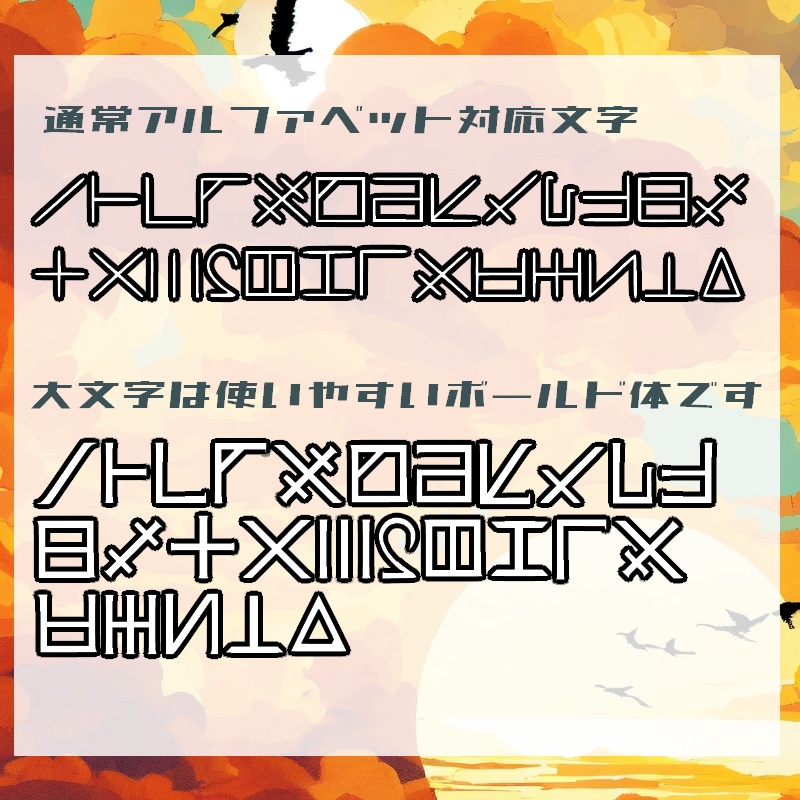
HYUPONIA FONT
『Hyuponia_Font』は風のクロノア2 世界が望んだ忘れ物 の作中,哀しみの国『フーポニア』で使用されている架空文字をフォントしたものです. 大文字は使いやすさ重視のアレンジボールド書体,小文字はゲーム中で哀しみの王様がスフィアに発現させている書体の再現になります. あくまで資料をやゲーム画面を元に再現したものですので,再現性の保証はしかねます. ご使用の際はその点を留意していただけると助かります. クロノア作品での創作活動などにお役立ていただけると幸いです. 対応文字や細かい仕様については同封のreadmeテキストを参照してください. 尚,このフォントは更新により内容が旧版から変化することがありますがご了承ください. (現行最新版はVer3です) =========================================== このフォントはデザイン用途にご使用いただけます. 【利用規約】 ・印刷物,映像作品,グッズ作成等での利用はOK ・ロゴマーク等への画像への加工使用もOK ・スクリーンショット/撮影/公開はOK ・改変/再配布/自作発言はNGです 利用報告は必須ではありませんが,報告してくれると作者が喜びます.